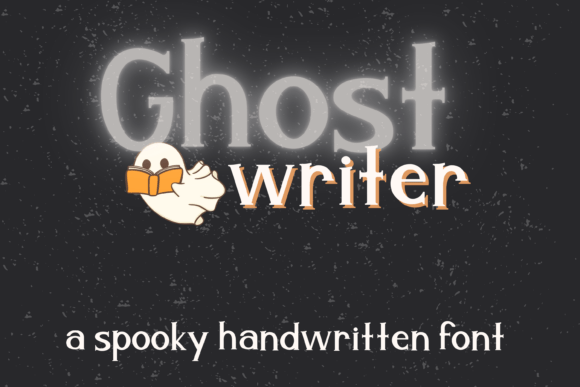
Ghost Writer
適切なデザイン要素を見つけるのは難しい場合がありますが、Ghost Writerは作品を即座に引き立てる優れたコレクションを提供します。
POD(オンデマンド印刷)製品、結婚式の招待状、またはソーシャルメディアのグラフィックを作成している場合でも、Ghost Writerは理想的です。